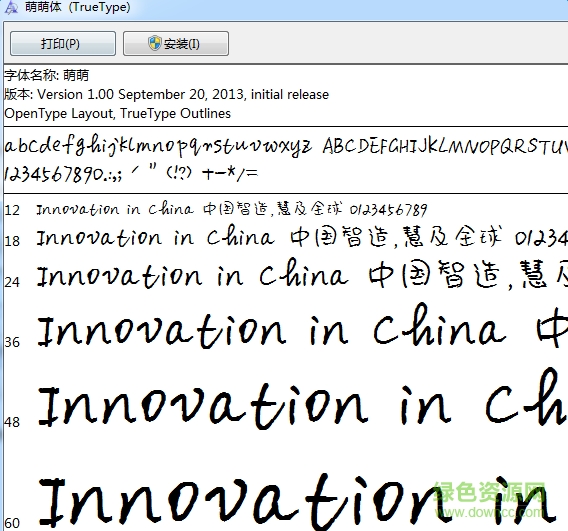
软件介绍 软件标签: 其他字体 字体 伯乐自然萌体字体是一款超好用的中文个性字体,该字体非常萌,给用户的平面设计带来了一丝活力,让广告宣传更有效,欢迎来绿色资源网下载。伯乐自然萌体字体安装方法方法一:控制面板/字体/文件/安装新字体;方法二:直接将字体复制到C:\WINDOWS\Fonts。方法三:针对win7系统,用户只需选中字体右键安装即可。注意事项本站所有字体资源仅供个人学习与参考,如需商业使用请到相关官网授权。小编测评伯乐自然萌体字体是一款极具个性的字体,该字体十分飘逸,彰显了自己的个性,有喜欢的朋友可以来绿色资源网下载使用! 软件截图 上一张下一张(1 / 1) 安装详细截图 猜你喜欢 伯乐字体 伯乐字体 伯乐字体是一款非常好看的字体,字体整体非常的优雅细腻,极具手写风格特色,非常适合用于包装印刷和广告设计,艺术感非常的浓郁,使用起来也非常的方便! 查看更多>> 伯乐丫丫体字体ttf 2.40M/中文/10.0/加粗版下载 伯乐俏皮体 2.12M/中文/5.0/下载 伯乐花香软妹体 2.12M/中文/10.0/补全版下载 伯乐小清新体 2.16M/中文/10.0/下载 伯乐竹笋体ttf(伯乐字库) 1.99M/中文/10.0/下载 伯乐学渣字体ttf 2.19M/中文/5.0/下载 其他版本下载 标题 大小 更新日期 下载 下载地址 电脑版 伯乐自然萌体 点击报错 软件无法下载或下载后无法使用,请点击报错,谢谢! 关闭报错反馈 请描述您所遇到的错误,我们将尽快予以修正,谢谢! *必填项,请输入内容 本类最新 dreamweaver字体库 首尔南山体字体 v1.06 官方版 潮字社风云简ttf 潮字社凌渡鲲鹏简体字体 潮字社曾玉波手书简字体 微博慧心字体 相关文章 Photoshop字体安装使用方法和技巧 如何解决“无法新增字体”问题 Win 7系统安装字体方法 网页字体大小设置方法 怎么改网页字体大小 在Linux系统中安装字体的几种方法 windows7字体显示问题:打开某些程序的时候显示的是乱码 用户评论 热门评论 最新评论 发表评论 查看所有评论(0) 昵称: 请不要评论无意义或脏话,我们所有评论会有人工审核. 字数: 0/500 (您的评论需要经过审核才能显示)